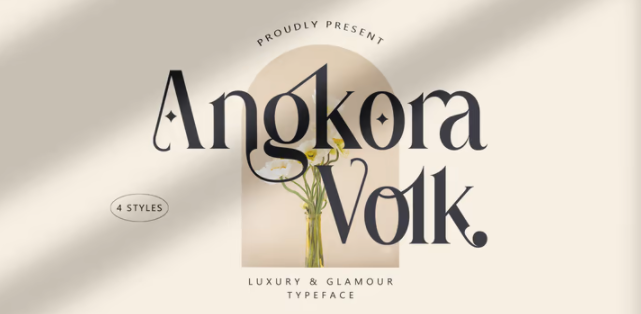
Angkora Volk - стильный богатый шрифт OpenType с буквами, которые словно танцуют и кружатся в гармонии, образуя уникальный и элегантный шрифтовой дизайн.
Большой выбор переплетений и замен OpenType, что означает большой выбор и разнообразие в вашем конечном виде.
В комплект входит широкий спектр полезных глифов - см. предварительные изображения всех глифов.